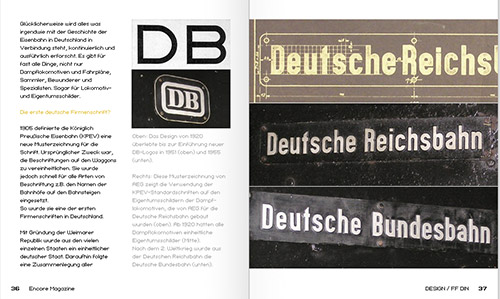
Geschichte der DIN-Schrift (encore)In der gerade erschienenen Ausgabe 13 der Online-Blätterzeitschrift
encore finden wir Folge 1 einer exklusiven
Serie über die Geschichte der DIN-Schrift. Der Schriftentwerfer
Albert-Jan Pool hat sie verfasst und bemerkenswertes Bildmaterial aus
deutschen Archiven gefördert. Die 8-seitige Story beginnt auf Seite 32.
![]() Albert-Jan Pool ist ein ausgesprochener DIN-Kenner. Als Entwerfer
der FF DIN (1995) hat er sich intensiv mit dem
Aussehen der Schrift auseinandergesetzt. Sein Interesse an der Vergangenheit der
Schrift ist aber erst in jüngster Zeit erwacht. Er durchforstete Museen und
Archive, um dem Ursprung der deutschen Industrieschrift auf den Grund zu
gehen.